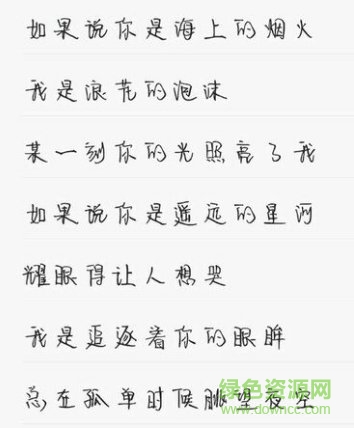
丁丁兩小無(wú)猜字體
兩小無(wú)猜字體是丁丁系列字體的特色手寫字體,有著純凈而柔和的筆觸,給人朦朧的現(xiàn)世安然感,字體行間跳動(dòng)的都是傾心的喜悅,讓人印象深刻,來(lái)綠色資源網(wǎng)下載即可使用!
丁丁兩小無(wú)猜字體介紹
妾發(fā)初覆額,折花門前劇,郎騎竹馬來(lái),繞床弄青梅,同居長(zhǎng)干里,兩小無(wú)嫌猜。
兩小無(wú)猜,指的是男女小時(shí)候在一起玩耍,天真爛漫,沒(méi)有猜疑,也形容男女從小感情好,純真的感情。
丁丁兩小無(wú)猜加粗版特色
兩小無(wú)猜加粗版、兩小無(wú)猜改小版都是在原字體上的處理而來(lái),使用常規(guī)的加粗設(shè)置可以讓文字變得碩大,給人更加清晰的視覺(jué)體驗(yàn),可以運(yùn)用在廣告創(chuàng)意、藝術(shù)設(shè)計(jì)等領(lǐng)域!